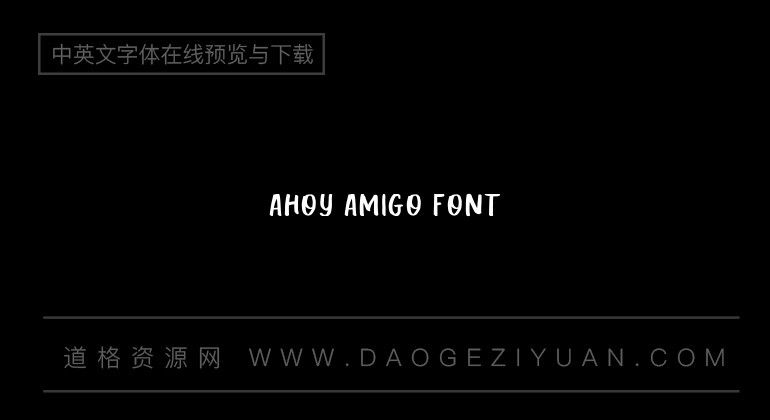
Ahoy Amigo Font
Ahoy Amigo是一种装饰艺术字体,它的设计灵感来自于传统的手绘广告和海盗文化。该字体由设计师Tobias Saul设计,是一种带有手工感的艺术字体,字母之间有一些自然的波动和变形,使得字体看起来更加生动有趣。Ahoy Amigo字体适用于海洋、冒险、旅游、餐饮等场景,可以用于海报、标志、包装等设计中,给人带来一种独特而有趣的感觉。
Ahoy Amigo Font是一款非常不错的手写艺术字体,具有很好的视觉感,适合于文化类的宣传设计、商业类品牌的广告和产品包装设计以及个性化文字排版等较多场景。